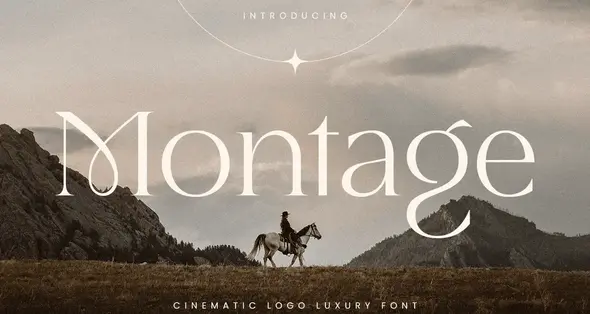
• Montage - Cinematic Logo Luxury Font
فونت انگلیسی سینمایی
• circle سبک قلم: Serif
مونتاژ یک فونت لوکس سینمایی است که برای افزودن ظرافت و پیچیدگی به پروژه‌های طراحی سطح بالای شما طراحی شده است. با الهام از زیبایی جاودانه سینمای کلاسیک، مونتاژ زیبایی‌شناسی مدرن را با لمسی از زرق و برق وینتیج ترکیب می‌کند. این فونت برای ساخت لوگوهای خیره‌کننده و مواد برندینگ نفیس ایده‌آل است و برای طراحانی که می‌خواهند با کارهای خود بیانی جسورانه داشته باشند، عالی است.
مونتاژ از اشتیاق به دوران طلایی سینما متولد شد، جایی که هر فریم با دقت و توجه به جزئیات ساخته می‌شد. این فونت آن روح را به تصویر می‌کشد و ترکیبی از ظرافت و مدرنیته را ارائه می‌دهد که مطمئناً هر پروژه‌ای را ارتقا می‌بخشد. چه برای برندهای لوکس طراحی کنید، چه پوسترهای سینمایی بسازید یا لوگوهای شیک طراحی کنید، مونتاژ تعادل کاملی از پیچیدگی و خلاقیت را فراهم می‌کند.
ویژگی‌های فونت مونتاژ:
• طراحی ظریف: ایده‌آل برای برندینگ لوکس، پوسترهای سینمایی و پروژه‌های سطح بالا
• کاربرد چندمنظوره: مناسب برای لوگوها، برندینگ، عنوان‌ها و طراحی‌های شیک
• خوانایی بالا: تضمین می‌کند که پیام شما به طور مؤثر با حروف واضح و شارپ منتقل شود
• جذابیت سینمایی: زیبایی‌شناسی مدرن را با لمسی وینتیج ترکیب می‌کند تا ظاهری منحصر به فرد و به یاد ماندنی ایجاد کند
• پیش‌نمایش‌های الهام‌بخش: شامل طرح‌های نمونه برای برانگیختن خلاقیت شما و نمایش پتانسیل فونت
مناسب برای:
• برندینگ لوکس: ساخت لوگوهای ظریف و به یاد ماندنی برای برندها و کسب‌وکارهای سطح بالا
• پروژه‌های سینمایی: طراحی پوسترهای فیلم چشم‌نواز، سکانس‌های عنوان و مواد تبلیغاتی
• مواد حرفه‌ای: توسعه کارت ویزیت، سربرگ و لوازم التحریر اداری شیک و پیچیده
• بازاریابی و تبلیغات: ارتقاء بروشورها، تبلیغات و کمپین‌های دیجیتال با لمسی از لوکس بودن
Montage is a cinematic luxury font designed to bring elegance and sophistication to your high-end design projects. Inspired by the timeless beauty of classic cinema, Montage combines modern aesthetics with a touch of vintage glamour. Ideal for creating stunning logos and refined branding materials, this font is perfect for designers who want to make a bold statement with their work.
The Story Behind Montage:
Montage was born from a passion for the golden age of cinema, where every frame was crafted with care and attention to detail. This font captures that spirit, offering a blend of elegance and modernity that is sure to elevate any project. Whether you're designing for luxury brands, creating cinematic posters, or crafting stylish logos, Montage provides the perfect balance of sophistication and creativity.
Montage Font Features:
Elegant Design: Perfect for luxury branding, cinematic posters, and high-end projects.
Versatile Usage: Ideal for logos, branding, headlines, and stylish designs.
High Legibility: Ensures your message is communicated effectively with clear and sharp lettering.
Cinematic Appeal: Combines modern aesthetics with a vintage touch to create a unique and memorable look.
Inspirational Previews: Includes sample designs to spark your creativity and show the font's potential.
Perfect For:
Luxury Branding: Create elegant and memorable logos for high-end brands and businesses.
Cinematic Projects: Design eye-catching movie posters, title sequences, and promotional materials.
Professional Materials: Develop stylish and sophisticated business cards, letterheads, and office stationery.
Marketing and Advertising: Enhance brochures, advertisements, and digital campaigns with a touch of luxury.
Elevate your design projects with Montage and bring a touch of cinematic luxury to your work.